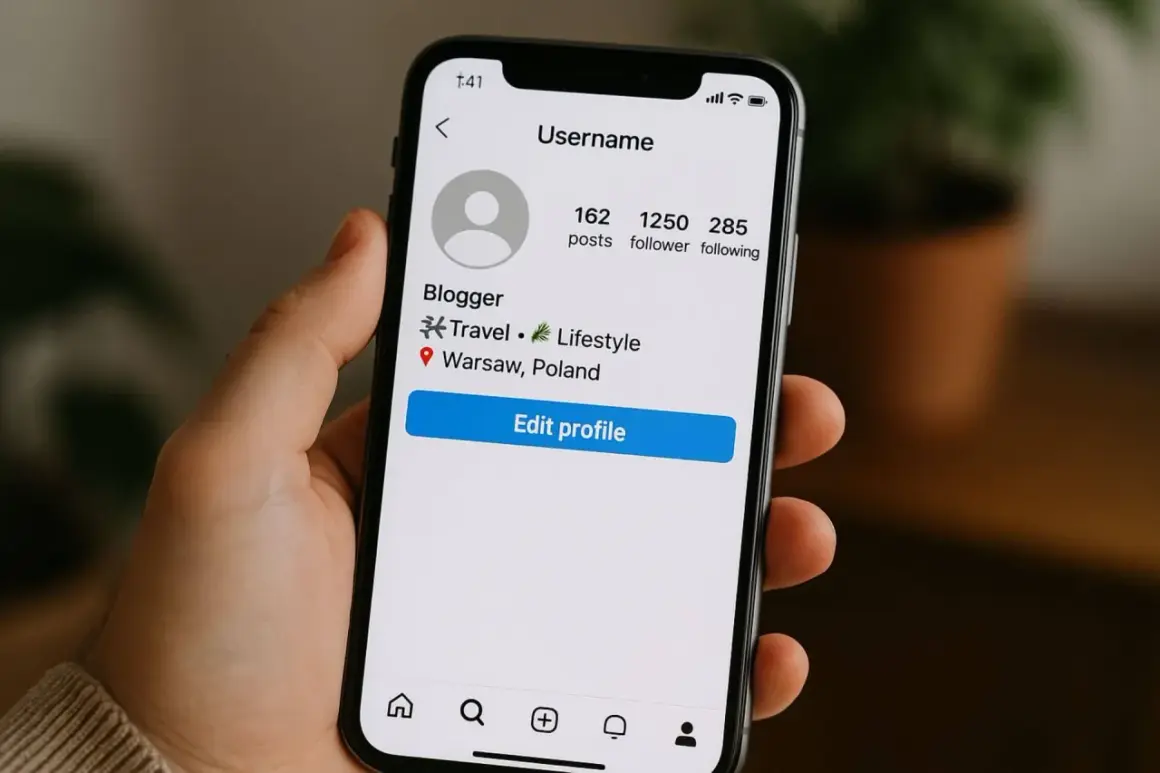
Typografia na Instagramie decyduje o tym, czy komunikat da się przeczytać od razu, czy trzeba się w niego wpatrywać jak w źle złożony plakat. W praktyce temat obejmuje trzy różne rzeczy: wbudowane style tekstu w Stories i Reels, ozdobne znaki kopiowane z generatorów oraz klasyczne zasady doboru kroju do bio, opisów i grafik. To właśnie te różnice najczęściej przesądzają, czy profil wygląda spójnie i profesjonalnie.
W skrócie, na Instagramie wygrywa czytelność, nie fajerwerki
- Instagram ma własne, wbudowane style tekstu w Stories i Reels, ale to nie jest pełny katalog fontów.
- Ozdobne litery z generatorów to zwykle znaki Unicode, a nie prawdziwa zmiana czcionki.
- Najlepiej działają krótkie akcenty, a nie długie bloki dekoracyjnego tekstu.
- W bio i opisach najbezpieczniej sprawdza się prosty system: 1 font podstawowy i 1 akcentowy.
- Jeśli grafika ma być czytelna na telefonie i w druku, prostota zwykle daje lepszy efekt niż modne ozdobniki.
Jakie fonty Instagram daje w samej aplikacji
Instagram ma własny krój pisma, Instagram Sans, ale użytkownik nie wybiera go jak z katalogu fontów. W samej aplikacji dostajesz raczej ograniczony zestaw stylów do napisów w Stories, Reels i innych narzędziach edycyjnych. Oficjalnie sprowadza się to do prostego mechanizmu: dodajesz tekst, a potem przesuwasz palcem w lewo lub w prawo, żeby zmienić jego styl.
| Miejsce | Co realnie da się zrobić | Najlepsze zastosowanie | Ograniczenia |
|---|---|---|---|
| Stories | Wbudowane style tekstu, kolor, pozycja, wielkość | Krótki hook, CTA, cytat, wyróżnienie kluczowego słowa | Liczba stylów jest ograniczona i może się różnić po aktualizacji aplikacji |
| Reels | Zmiana stylu fontu w edytorze i napisy na wideo | Napisy do krótkich ujęć, akcenty w montażu, prosty przekaz | To nie jest pełny edytor typograficzny |
| Edytory Meta | Wybór stylu tekstu w projekcie | Rolki i materiały, w których tekst ma wspierać obraz | Swoboda nadal jest mniejsza niż w programie graficznym |
| Bio i opis profilu | Zwykły tekst, emoji, łamanie linii | Krótka, czytelna prezentacja konta | Brak natywnej galerii fontów |
Gdy patrzę na to praktycznie, Instagram daje wystarczająco dużo swobody do akcentów, ale nie do budowania całej identyfikacji wyłącznie w aplikacji. Jeśli tekst zaczyna konkurować ze zdjęciem, to znak, że font jest już zbyt mocny albo źle użyty. I właśnie dlatego kolejny poziom to ozdobne znaki kopiowane z generatorów.
Gdzie działają fonty kopiowane z generatorów Unicode
To, co wiele osób nazywa „zmianą czcionki”, najczęściej jest tylko innym zapisem liter z Unicode. Unicode to standard znaków tekstowych, dzięki któremu litery mogą wyglądać jak pogrubione, kursywne, w małych kapitalikach albo bardziej dekoracyjnie, mimo że technicznie nadal są tekstem, a nie nowym fontem.
| Styl | Gdzie się sprawdza | Kiedy lepiej odpuścić |
|---|---|---|
| Pogrubiony lub kapitaliki | Bio, nagłówek, jedno mocne wyróżnienie | W długim opisie, gdzie liczy się płynność czytania |
| Kursywa lub styl elegancki | Krótki cytat, marka premium, subtelny akcent | W instrukcjach i treściach, które mają być szybkie w odbiorze |
| Monospace | Konta techniczne, backstage, komunikaty o procesie | W profilu lifestyle, jeśli styl ma być ciepły i miękki |
| Bubble, old English, odwrócone litery | Zabawne akcenty, pojedyncze słowa, krótkie kampanie | W profesjonalnym bio, w którym liczy się wiarygodność |
Tu kluczowe jest jedno rozróżnienie: ozdobne znaki nie zawsze zachowują się tak samo na każdym urządzeniu. Im bardziej egzotyczny styl, tym większe ryzyko, że coś zmieni się w odstępach, wyglądzie albo czytelności. Dlatego zawsze sprawdzam polskie znaki, bo ą, ę, ł, ó, ś, ż, ź, ć i ń potrafią najszybciej zdradzić, że tekst wygląda dobrze tylko w podglądzie generatora.
Tak samo ostrożnie podchodzę do hashtagów i nazwy profilu. Tam ozdobne litery zwykle nie są dobrym pomysłem, bo łatwo tracą czytelność i przestają pełnić swoją funkcję. Jeśli zależy Ci na spójnym wizerunku, Unicode traktuj jako przyprawę, nie jako bazę całego dania. A skoro już wiesz, gdzie działa trik, trzeba jeszcze odpowiedzieć na ważniejsze pytanie: co wybrać dla konkretnego profilu.
Jak dobrać typografię do bio, opisów i grafik
W typografii na Instagramie najczęściej wygrywa zasada jednego języka wizualnego. Ja zwykle trzymam się dwóch rodzin krojów maksymalnie: jednej neutralnej do treści i jednej bardziej charakterystycznej do nagłówków albo krótkich akcentów. To wystarcza, żeby profil wyglądał konsekwentnie, a nie jak zbiór przypadkowych pomysłów.
| Cel | Co działa najlepiej | Czego unikać |
|---|---|---|
| Portfolio fotografa | Prosty sans serif do opisów, elegancki serif do nagłówków grafik | Zbyt dekoracyjnych liter, które odciągają uwagę od zdjęć |
| Marka osobista | Jasny, czytelny font i jeden mocniejszy akcent w bio | Mieszania kilku ozdobnych stylów w jednym profilu |
| Konto promocyjne lub eventowe | Mocny font display tylko w nagłówku, prosty tekst pomocniczy | Dużych bloków tekstu w stylu „bąbelkowym” |
- Test na telefonie, zanim publikacja trafi do sieci.
- Kontrola polskich znaków, żeby efekt nie rozpadł się na najprostszych literach.
Jeżeli ten sam projekt ma później trafić także do druku, dodałbym jeszcze jedną wersję z większym kontrastem i prostszą typografią. Na ekranie ozdoba może wyglądać dobrze, ale papier i mały ekran szybko pokazują, czy krój naprawdę pracuje na treść. To właśnie taki spokojny, konsekwentny układ najczęściej daje profilowi więcej klasy niż najbardziej efektowny generator fontów.